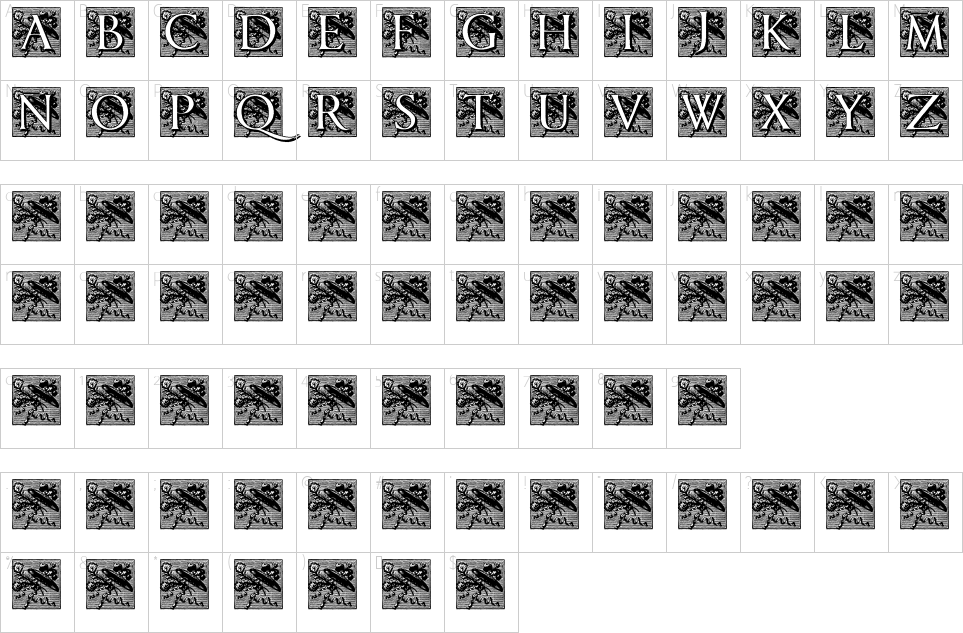
A fonte Pompadour Initials é uma criação visionária do designer Paul Lloyd, disponível gratuitamente para download tanto no Windows quanto no Mac. Esta fonte é especialmente adequada para criar um estilo tipográfico único, com linhas suaves e elegantes que garantirão um toque sofisticado a qualquer design. Com sua beleza artística e versatilidade, Pompadour Initials é um recurso indispensável para designers gráficos, ilustradores e criadores de materiais digitais que desejam adicionar uma textura única a seus projetos. Download a sua cópia agora e experimente o poder desta fonte única. Com apenas quatro milhares de downloads, Pompadour Initials é um recurso que não pode ser deixado de fora de sua coleção de fontes.